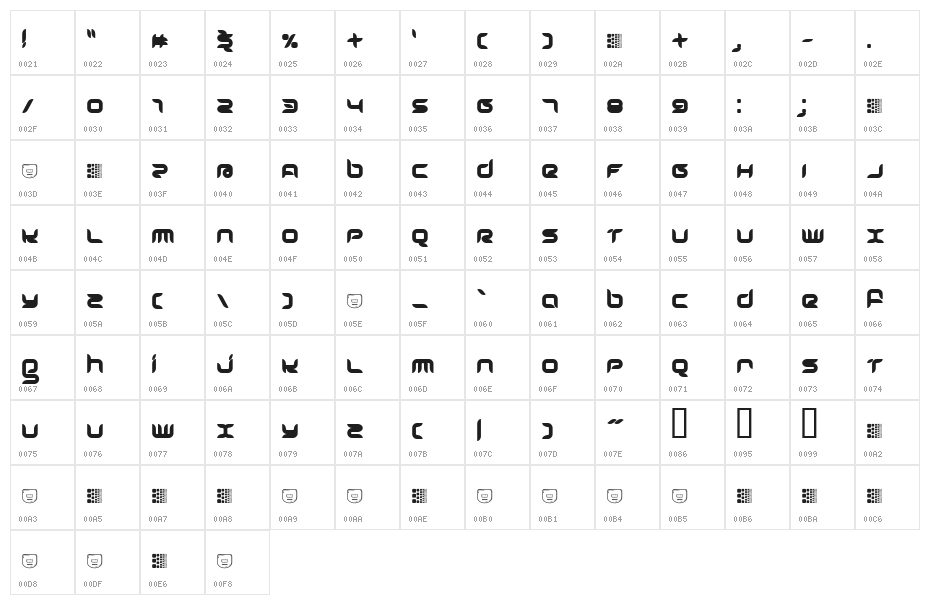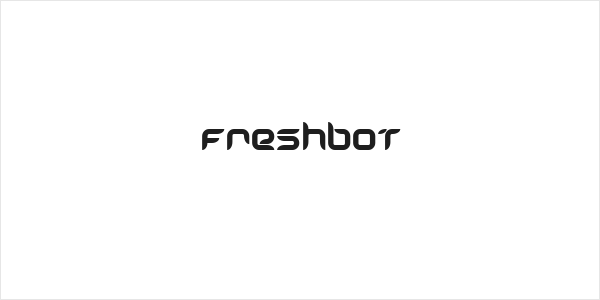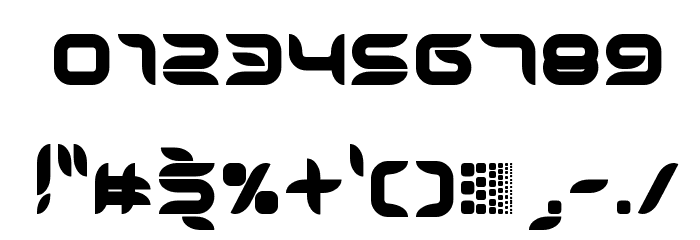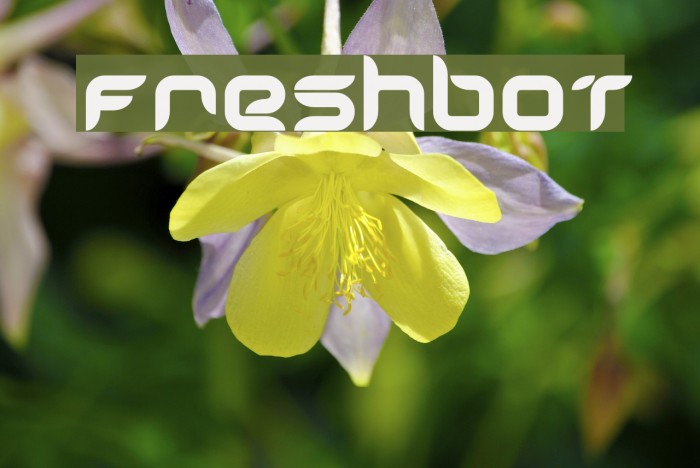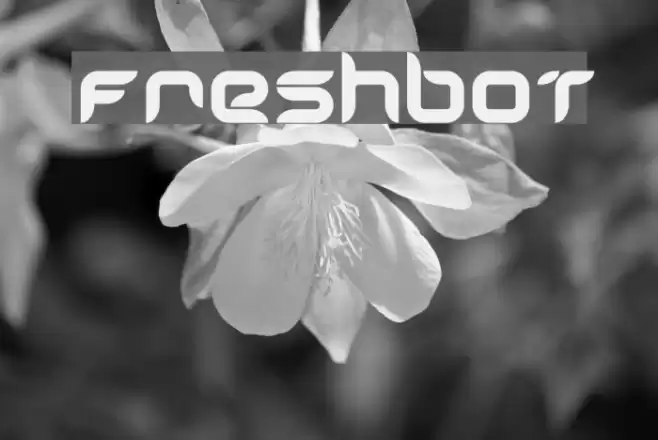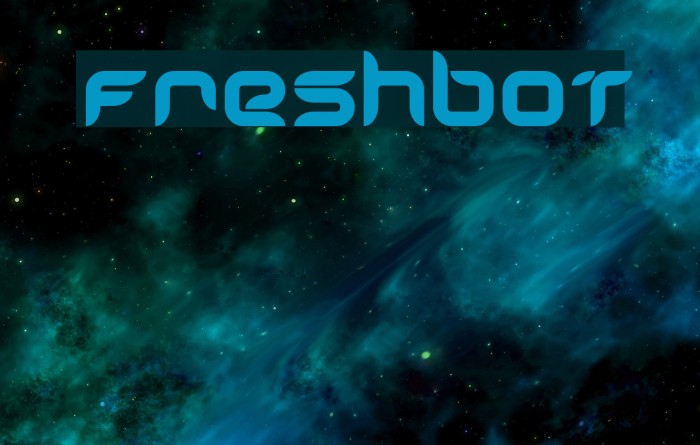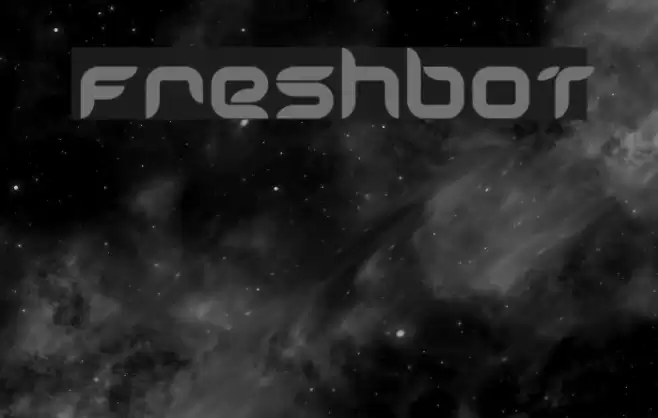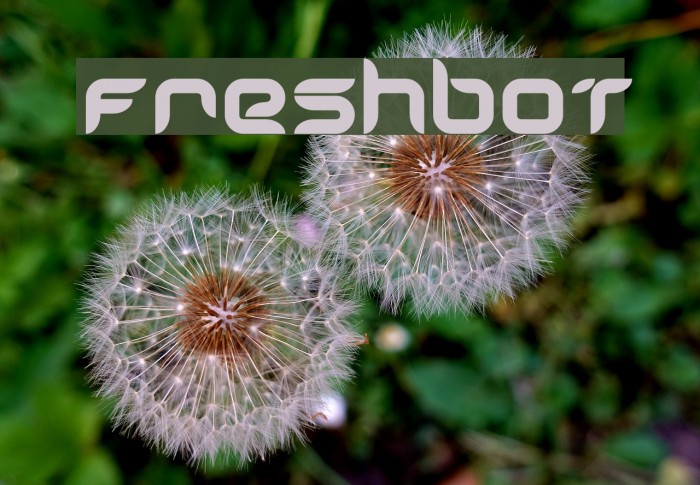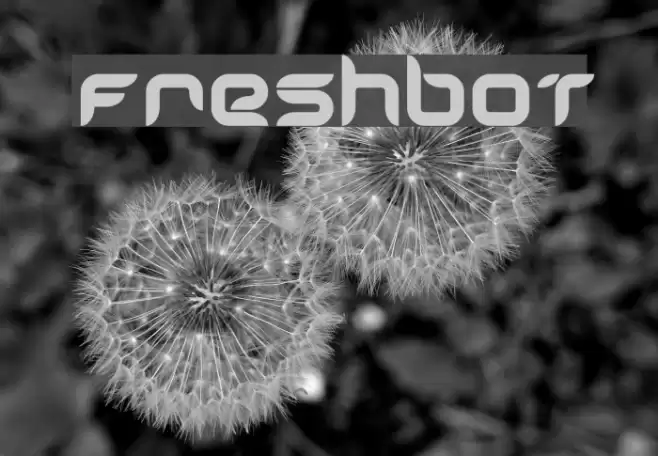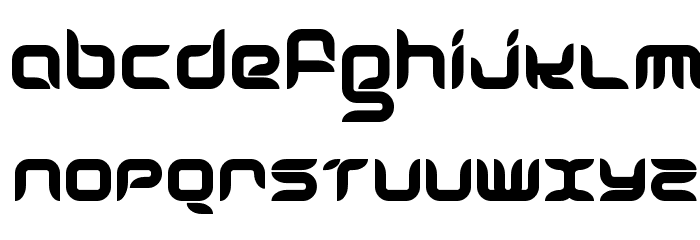
Freshbot Font
| Cas d'utilisation | Logos, Headlines |
| Projets proposés | Ideal for technology branding, modern advertising, and creative digital content. |